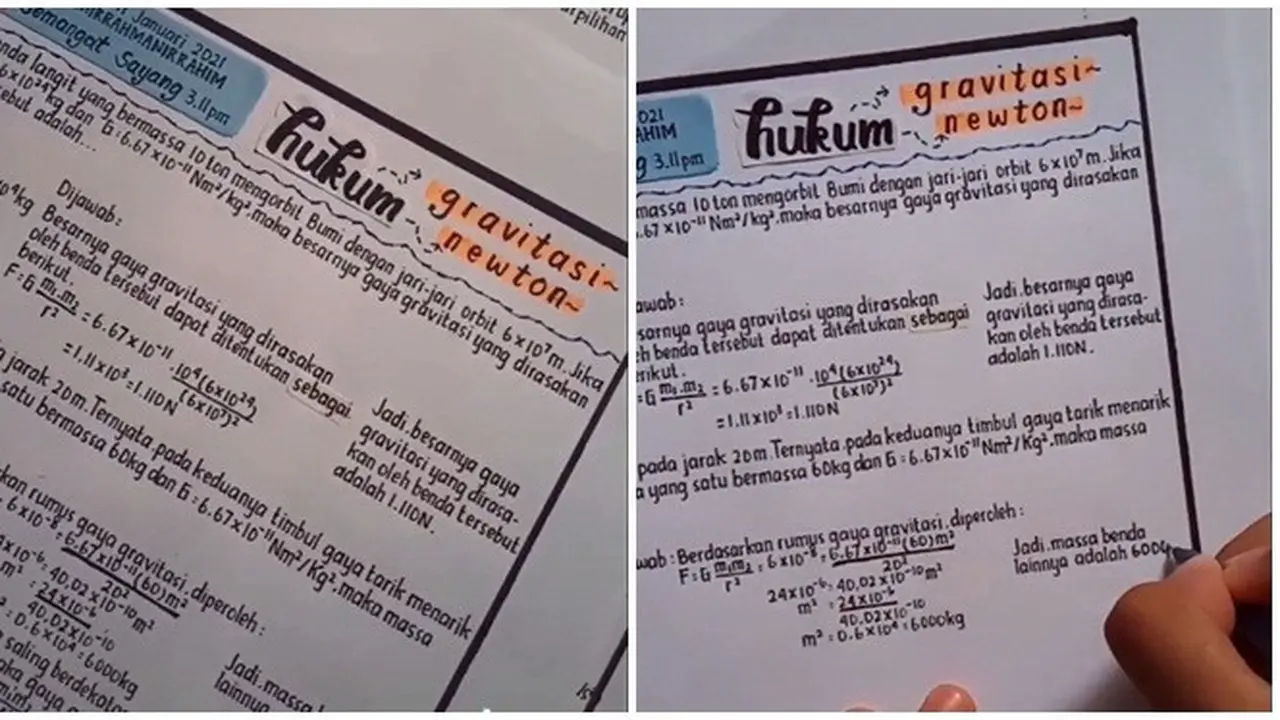
Liputan6.com, Jakarta Memiliki tulisan yang sangat rapi dan menarik menjadi sebuah keinginan bagi banyak orang. Pasalnya, dengan melihat tulisan yang rapi dan menarik mampu membuat kamu untuk semangat belajar. Namun, tentu saja perlu usaha yang cukup untuk memiliki tulisan rapi.
Akan tetapi, baru-baru ini beredar di media sosial adanya seorang siswa SMA yang menunjukkan tulisan tangan begitu rapi. Melalui akun TikTok @almafns, siswa SMA tersebut membagikan beberapa video soal tulisan tangan yang sangat rapi saat mengerjakan tugas dan merangkum materi.
Video tulisan siswa SMA yang diketahui berasal dari Cilacap, Jawa Tengah ini pun langsung menarik perhatian publik. Bahkan, tak sedikit pula netizen yang memuji tulisan-tulisan tangah siswa tersebut.
Video dari akun TikTok @almafns ini pun langsung viral di berbagai media sosial. Bukan hanya menunjukkan hasil tulisan tangannya saja, akan tetapi ia juga memberikan beberapa tips untuk menulis tangan yang rapi.
Bak ketikan komputer
Melalui akun TikTok @almafns, ia pun beberapa kali membagikan hasil tulisannya saat tengah mengerjakan tugas dan rangkuman materi. Namun, tulisan milik Siswa SMA bernama Alma tersebut justru menarik perhatian publik. Pasalnya, tak sedikit netizen yang menyebut jika tulisan milik Alma terlihat bak ketikan komputer.
Bukan hanya membagikan beberapa catatan tugas dan rangkuman materi saja. Alma bahkan memberikan tutorial cara menulis yang rapi. Mulai dari sabar dan niat, menggunakan pulpen yang nyaman dan bagus versi diri sendiri, menulis setiap hari pada buku bergaris minimal satu kalimat, mengatur spasi setiap kata, menggunakan label dibanding tipe-x saat salah kata. Selain itu, menurutnya tulisan rapi bukan harus lurus ataupun sejajar. Melainkan bisa dibaca dan minim coretan dalam tulisan.
Respons netizen
Video soal tulisan tangan yang begitu rapi ini pun langsung mencuri perhatian netizen. Bahkan, tak sedikit pula yang merasa iri dengan hasil tulisan tangan siswa SMA tersebut. Beberapa video yang diunggah oleh akun TikTok @almafns mengenai tulisannya yang rapi ini bahkan telah dilihat jutaan kali. Berbagai respons netizen pun memenuhi kolom komentar video tersebut.